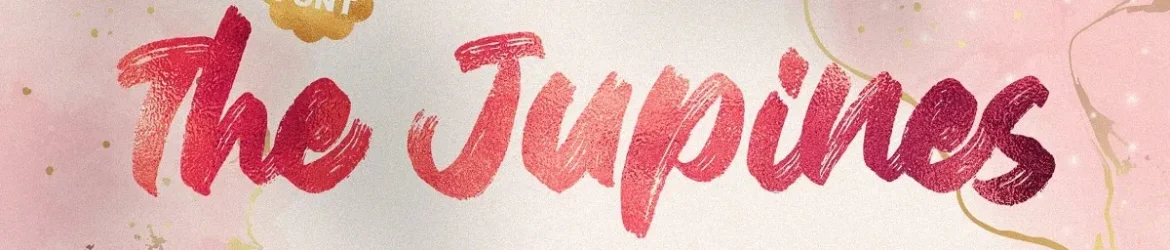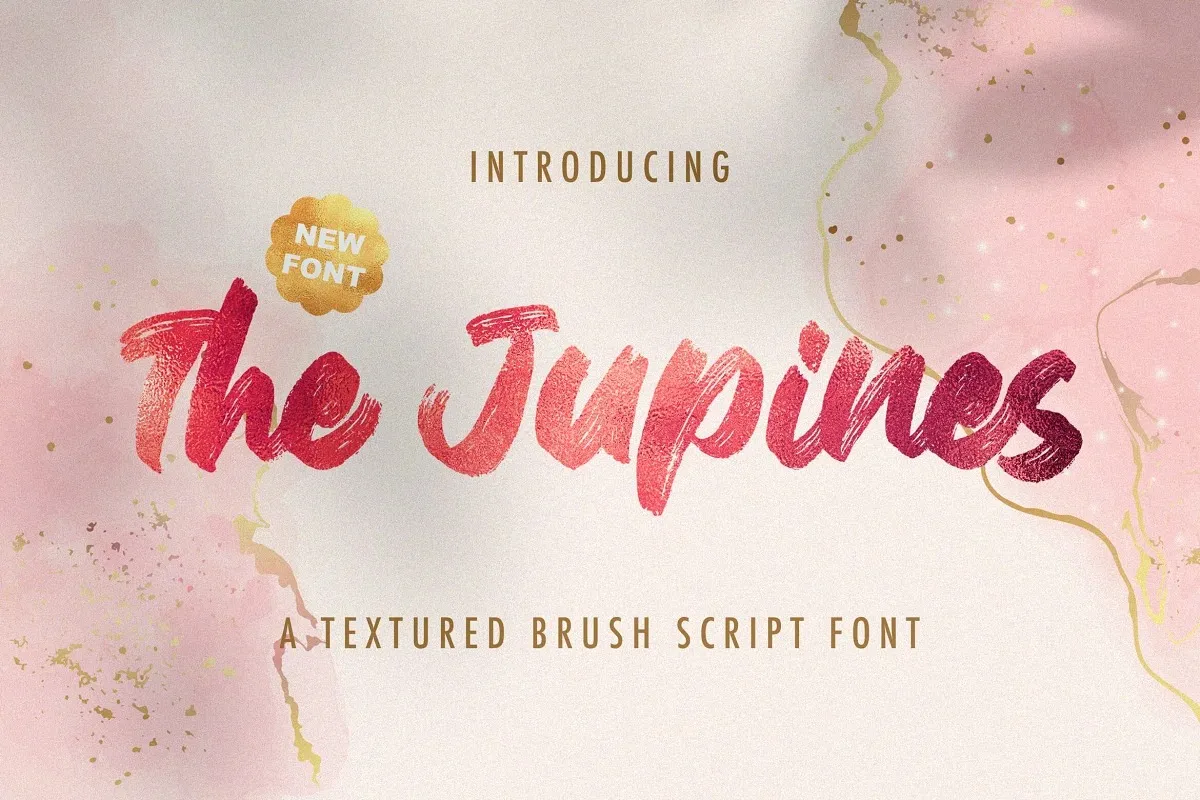
The Jupines Font – Fonte Grátis
The Jupines Font
A fonte The Jupines é perfeita para designers que buscam uma aparição casual e autêntica em seus projetos. Feita a partir de um traçado brush, ela oferece uma textura natural semelhante à tinta aplicada com uma esponja ou pincel. A The Jupines é especialmente apropriada para qualquer tipo de projeto que você possa imaginar, desde etiquetas e materiais publicitários até logotipos e slogans em camisas personalizadas. Uma das características mais interessantes da The Jupines é seu suporte à codificação PUA (Propaganda Unicode Assignment) e ao Multilinguismo básico, permitindo que ela atenda a um número vasto de demandas linguísticas. Essa fonte não apenas oferece uma variedade de tamanhos para uso em projetos digitais ou impressos, mas também sua textura única complementa perfeitamente qualquer projeto gráfico, tornando-a ideia ideal para branding, embalagens de produtos e até mesmo a criação de cartas de convite. A The Jupines é uma escolha segura se você está buscando um estilo script que combine autenticidade com simplicidade.